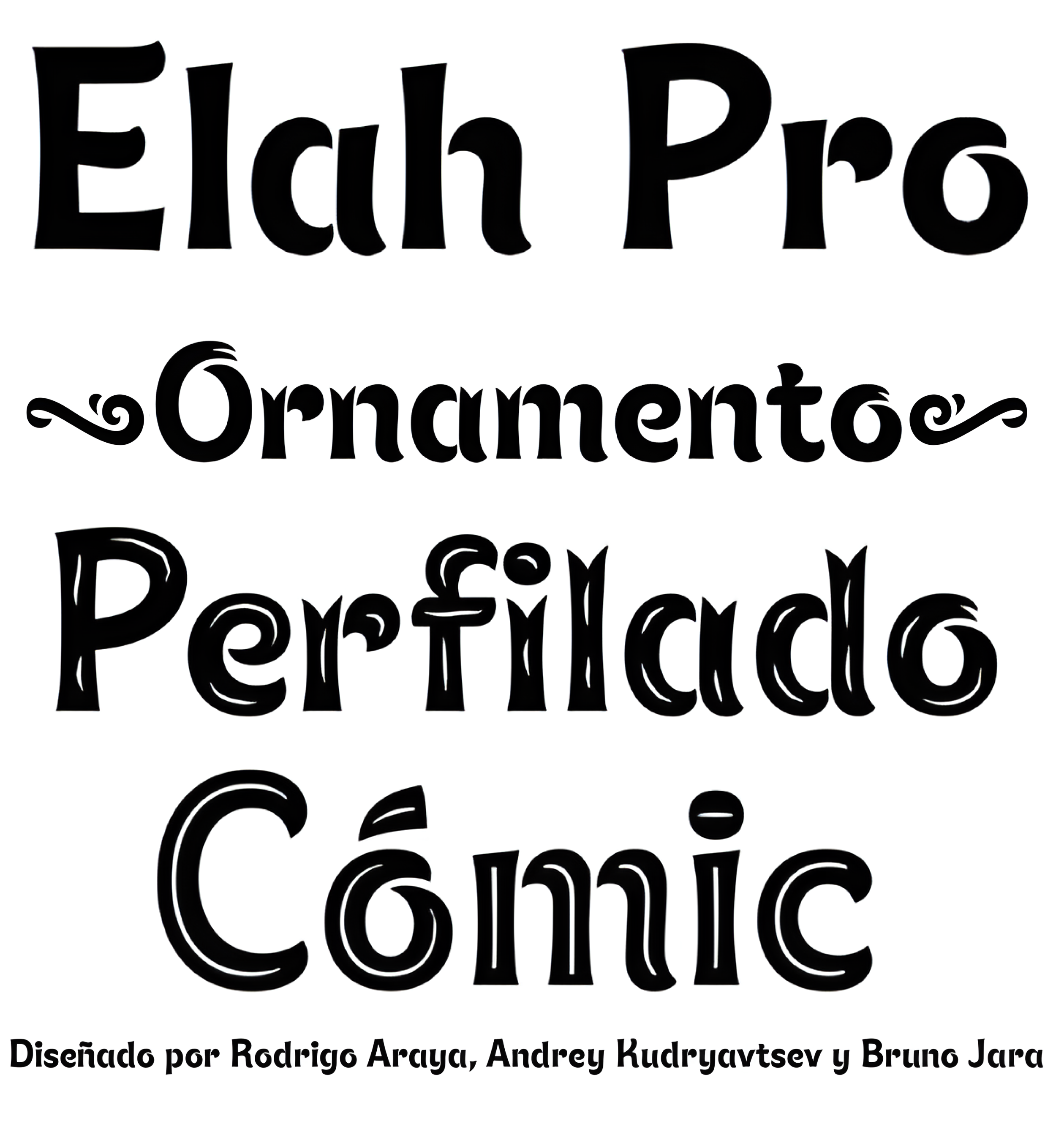
| Año | 2022 |
| Créditos | Andrey Kudryavtsev, Bruno Jara Ahumada |
| Descripción | La familia tipográfica Elah Pro fue diseñada por Andrey Kudryavtsev, Rodrigo Araya Salas, Bruno Jara Ahumada y publicada por RodrigoTypo. Elah Pro contiene 8 estilos y opciones de paquete familiar. Elah Pro es una Tipografía de Títulos, que contiene diferentes estilos como Ornamentos y Dingbats, especiales para jugar y combinar y hacer un título mucho más agradable y entretenido. |
| Familia(s) | Elah Pro Regular, Elah Pro Regular inline, Elah Pro Regular Tale, Elah Pro Regular Two , Elah Pro Regular XOrnament, Elah Pro XOrnament Tale, Elah Pro Regular YDingbats, Elah Pro Regular YDingbats Tale. |
| Estilos | 8 |
| Set | Especializado |
| Fundidora | RodrigoTypo |